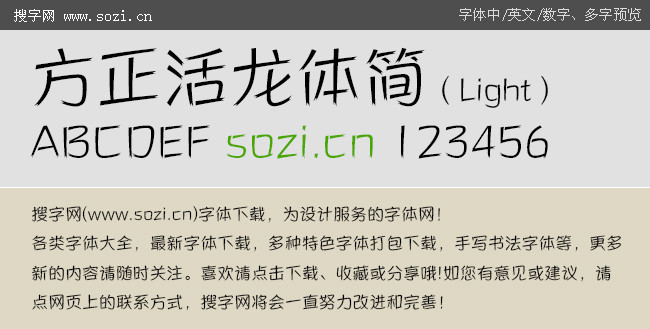
方正活龍?bào)w簡(jiǎn)Light
搜字網(wǎng)提供一款方正活龍?bào)w簡(jiǎn)中文字體下載,方正活龍?bào)w簡(jiǎn)是方正字庫(kù)全新開(kāi)發(fā)的一款非常實(shí)用的字體,該字體特點(diǎn)是橫、直劃粗細(xì)平均,所有筆劃頭部斜直而末端開(kāi)了叉口,而且點(diǎn),撇,捺,抅等都是弧形,沒(méi)有垂直平行線的,橫劃重心向右上方斜上,讓它活一些,有動(dòng)感和速度,像一條龍?jiān)谔炜诊w舞,可以應(yīng)用于網(wǎng)頁(yè)設(shè)計(jì)、包裝設(shè)計(jì)、海報(bào)設(shè)計(jì)等廣告設(shè)計(jì)場(chǎng)合使用。
• 風(fēng)格類別: 現(xiàn)代藝術(shù)體